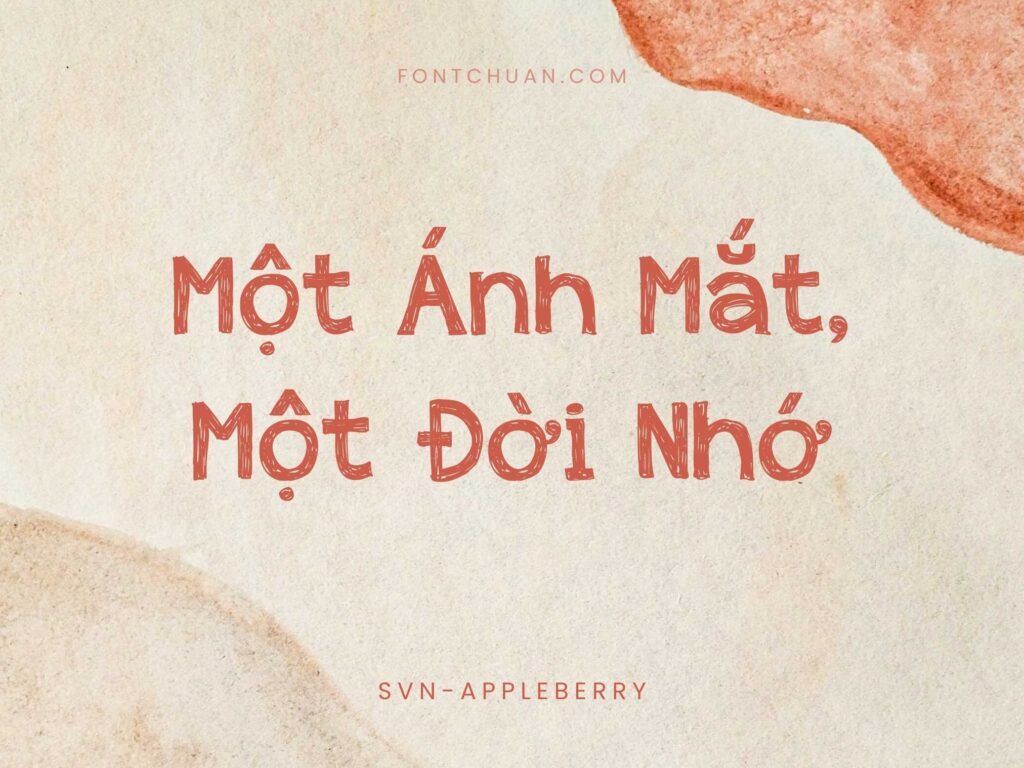
Font SVN Appleberry Việt Hóa
Appleberry là một font chữ viết tay phác thảo, được tạo ra bởi Brittney Murphy Design vào năm 2011. Font này mang phong cách chữ in khối với các đường nét cong và nét vẽ vui tươi, tạo nên sự thân thiện và hấp dẫn cho các thiết kế. Với 447 ký tự và hỗ trợ 65 ngôn ngữ dựa trên ký tự Latin, Appleberry cung cấp sự linh hoạt cho các nhà thiết kế trong việc tạo ra những tác phẩm độc đáo. Font đã được Việt hóa để hỗ trợ tiếng Việt bởi Styleno.1 Fonts, đồng thời hỗ trợ nhiều ngôn ngữ khác, giúp mở rộng phạm vi sử dụng trên toàn cầu. Font này được thành viên của Font Chuẩn sưu tầm và chia sẻ, đáp ứng nhu cầu của bạn đọc và ứng dụng thực tế vào các dự án thiết kế.
Đặc điểm thiết kế của Appleberry bao gồm các đường nét phác thảo thủ công, tạo cảm giác vui tươi và thân thiện. Font này phù hợp cho các ứng dụng như thiết kế đồ họa truyền thông xã hội, thiệp mời, thương hiệu và các thiết kế dành cho trẻ em. Các ngành nghề phù hợp bao gồm quảng cáo, giáo dục và nghệ thuật.